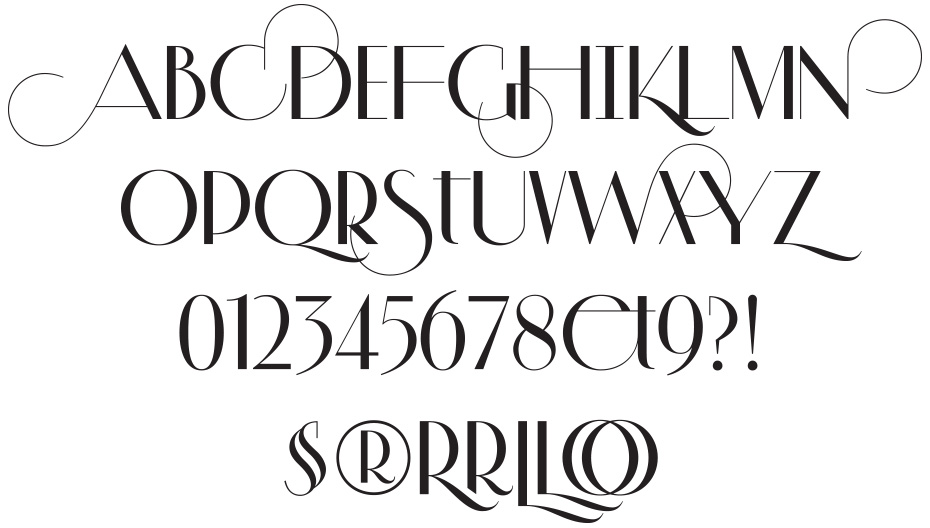
Шрифты онлайн для логотипа: Шрифты для логотипов онлайн – топ 3 сервиса для подбора
Шрифты для логотипов онлайн – топ 3 сервиса для подбора
Привет! В этой статье мы покажем онлайн сервисы которые помогают подобрать хороший шрифт для логотипа и облегчают задачу по сравнению и поиску правильного написания вашего названия в лого.
Бесплатные шрифты для логотипа.
Google создал удобный сайт для подбора шрифтов — https://fonts.google.com/ . На нем вы можете написать название собственной компании и сайт выдаст вам сотни вариантов для сравнения. Сервис удобен тем, что вы можете отфильтровать выдачу по желаемым параметрам. Например если у вас название бизнеса пишется русскими буквами — поставьте галочку напротив строчки «кириллица», и сайт будет показывать только русскоязычные шрифты. Также есть такие удобные параметры как жирность шрифта, его стиль (например рукописный, с засечками, моношрифт и т. д.) и другие особенности.
Сравнение скачанных шрифтов и Google шрифтов.
Незаменимым является сервис по сравнение уже скачанных к себе на компьютер шрифтов http://wordmark.it/ . Просто введите название вашей организации в строку на главной странице и нажмите кнопку Enter на клавиатуре. Сайт моментально покажет вам как будет выглядеть написание названия используя каждый шрифт, скачанный на ваш компьютер.
Также наверху вы можете нажать на кнопку Google Fonts, после чего сайт покажет вам, как будет смотреться нужный текст со всеми вариантами с сайта Google Fonts.
Вы можете помечать стили которые вам понравились после этого нажать на иконку сравнения в правом верхнем углу сайта. Вы попадете на страницу где будут показаны только понравившиеся шрифты для логотипа, чтобы вам удобно было сравнить их между собой и выбрать финальную версию.
Узнать что за шрифт на сайте.
Часто бывает, что вы находитесь на сайте и вам безумно понравился шрифт который на нем использовали. Раньше нужно было обращаться к знакомым дизайнерам в надежде на то, что они смогут определить его по написанию. Затем появились специальные онлайн сервисы, в которые можно было вставить скриншот с интересующего вас сайта и пройти несколько шагов в результате которых с вероятностью в 50% сервис выдавал вам название шрифта.
Если кликнуть на текст, то окошко с название расширится и вы увидите дополнительную информацию которая может оказаться для вас полезной.
На этом подборка онлайн сервисов подбора шрифта для логотипа закончена.
Надеемся теперь вы сможете без проблем подобрать красивый и бесплатный шрифт для вашего лого.
Шрифты для логотипов от дизайнеров на Behance (60+ бесплатно)
Поиграем со шрифтами?
В наши дни скачать и подобрать бесплатные шрифты для логотипов совершенно не сложно. Дизайнеры имеют невероятный выбор бесплатных шрифтов. Если вам необходимо подобрать шрифт для своего логотипа, эта статья именно для вас!
Подобранные шрифты подойдут для любого проекта, где нужно работать с типографией.
Все шрифты взяты с самого популярного творческого сайта для дизайнеров – Behance. Больше нет необходимости тратить свое время, чтобы найти подходящий шрифт для логотипа, мы уже выбрали лучшие из них для вас.
Для того чтобы скачать шрифт, нажимайте «Скачать» и листайте в самый низ презентации шрифта, там вы найдете ссылку. Также вы можете скачать все 60 шрифтов в одном архиве.
ДИСКЛЕЙМЕР. Данная подборка шрифтов составлялась нами вручную. Каждый шрифт можно скачать бесплатно. Внимание! Не все шрифты с этой подборки можно использовать для коммерческих целей. Пожалуйста, внимательно читайте описание на странице автора. Мы не несем ответственность за данную подборку. Авторы всех шрифтов указаны!
1.
FormForm – это шрифт без засечек, с различными диагональными вырезами. Шрифт подойдет для логотипов, плакатов, баннеров и брошюр.
2. Audrey
Шрифт «Audrey» является бесплатным шрифтом, он подходит для работы с логотипами, заголовками и типографической композицией. Прямые линии в шрифте создают контраст, а тонкость шрифта показывают его элегантность.
Как комбинировать шрифты логотипа?
Отличный дизайн, сочетающий в себе несколько разных шрифтов в одном логотипе.Дизайн логотипа Ага Очоко. При комбинировании разных шрифтов логотипа в одном дизайне логотипа вы хотите убедиться, что шрифты дополняют друг друга.